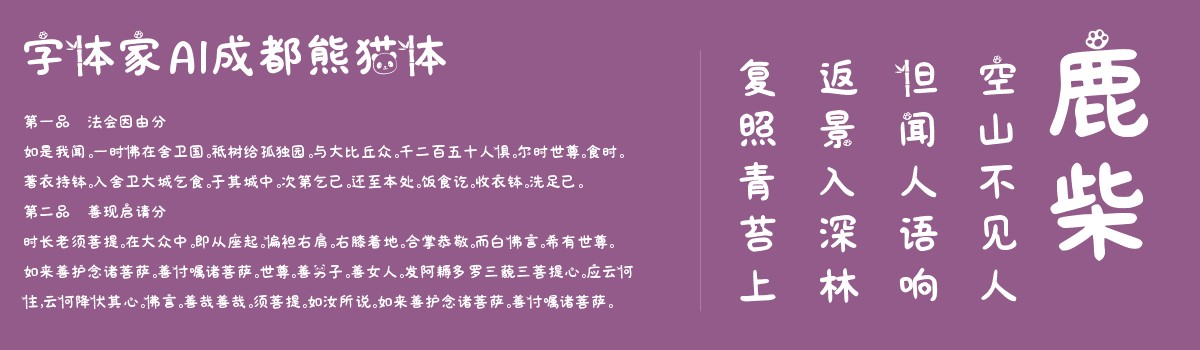
字体家AI成都熊猫体
字体家AI成都熊猫体这是一款由字体家AI神笔造字生成的艺术字体,充满了成都熊猫的活泼气息。这款字体在设计时充分融入了熊猫元素。点笔画变成了熊猫爪子,像小熊猫轻轻在纸上按下的印记;而单人旁摇身一变,化作翠绿的竹子,为整体增添了一种大自然的生机。
熊猫体不仅可爱,还极具实用性。无论是广告标题、平面文案,还是海报标题和网页广告,这款字体都能轻松胜任。每次浏览,它就像一只萌萌的小熊猫扑面而来,抓住你的注意力。如果你的设计作品需要一丝跳脱的乐趣与活泼的气息,AI成都熊猫体无疑是最佳选择。无论是引人注目的广告,还是充满趣味的文案,它都能让你的作品瞬间活起来!